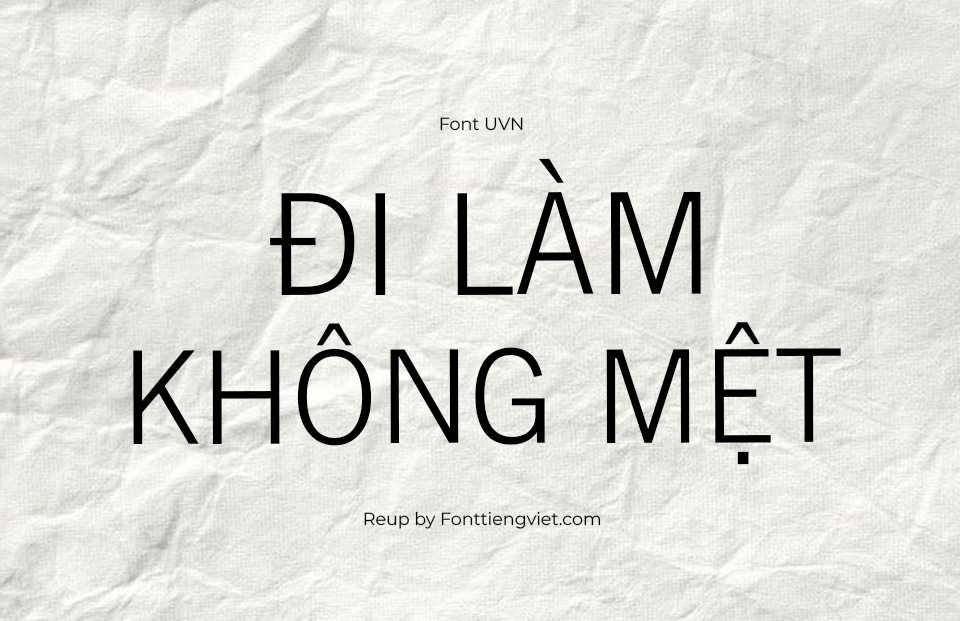
Tải Font Việt Hóa UVN Tin Tuc Nhe Miễn Phí Cho Thiết Kế Báo Chí
Trong thế giới đồ họa hiện đại, việc lựa chọn một Font Chữ phù hợp đóng vai trò quyết định đến tính thẩm mỹ và khả năng truyền tải thông điệp. Đặc biệt, bộ Font Việt Hóa UVN Tin Tuc Nhe nổi lên như một giải pháp hoàn hảo dành riêng cho các biên tập viên và nhà thiết kế nội dung tại Việt Nam. Được phát triển dựa trên tiêu chuẩn mã hóa Unicode, bộ font này không chỉ đảm bảo hiển thị tiếng Việt mượt mà mà còn mang lại cảm giác thanh thoát, dễ nhìn cho người đọc trên cả nền tảng in ấn lẫn kỹ thuật số.
Đặc điểm nổi bật của bộ Font Việt Hóa UVN Tin Tuc Nhe
Thiết kế tối ưu cho trải nghiệm đọc
Đúng như tên gọi, Font Việt Hóa UVN Tin Tuc Nhe sở hữu các đường nét mảnh mai nhưng vô cùng sắc nét. Cấu trúc chữ được tinh chỉnh để tối ưu hóa không gian hiển thị, giúp các bài viết dài trở nên thoáng đãng hơn. Điều này đặc biệt hữu ích trong môi trường học đường, khi các em học sinh cần trình bày báo tường hoặc tài liệu học tập một cách khoa học. Sự kết hợp giữa phong cách hiện đại và tính ứng dụng cao giúp bộ chữ này không bị lỗi thời theo thời gian.
Khả năng tương thích linh hoạt